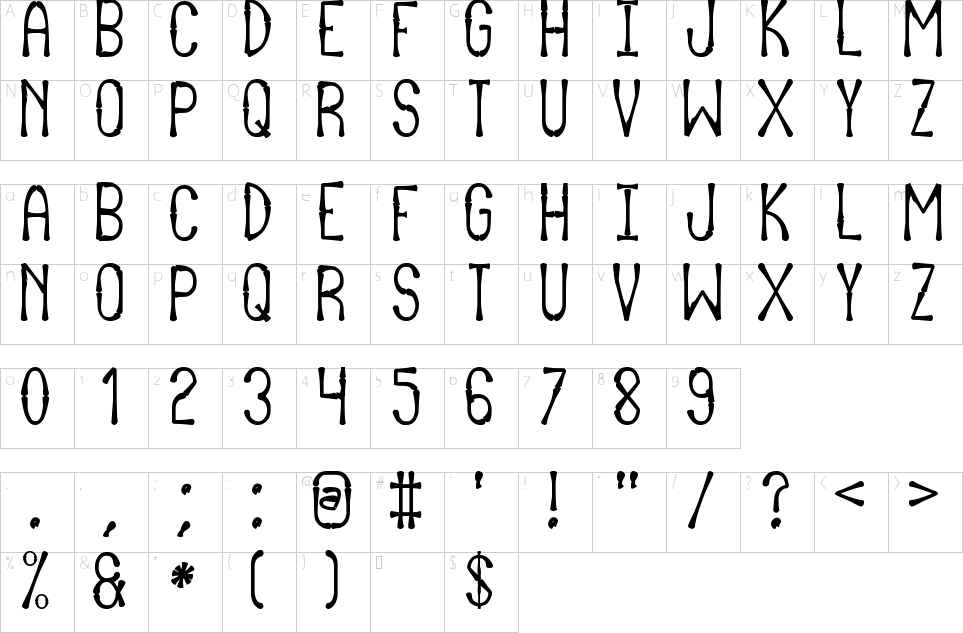
Afrika Safari Rebuild Font – Download Grátis
A fonte Afrika Safari Rebuild é uma criação de Southype, uma designer não muito famosa, mas cuja obra tem sido amplamente apreciada pelos criadores de materiais digitais. Esta fonte é uma atualização do design original do Afrika Safari, mantendo suas características icônicas e estilo único. Os criadores aprovam essa fonte como uma opção de fonte gratuita para uso em sites, aplicativos e outros projetos digitais. Com uma paleta de cores vibrante e uma tipografia que remete à atmosfera exótica do Afrika Safari, esta fonte é perfeita para designers que buscam uma fonte de estilo africano moderno e atraente. Ela foi baixada mais de 14.636 vezes, uma marca que ilustra a sua popularidade e qualidade. Se você está procurando uma fonte para seu próximo projeto, a Afrika Safari Rebuild é uma ótima escolha para um visual atraente e sem compromissos.